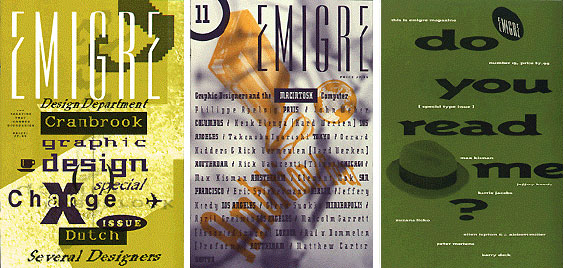
»Das Ende« von EmigreHeute erscheint zum 69. und letzten Mal das angesehene Designmagazin
»Emigre«, herausgegeben vom gleichnamigen Schriftenhaus –
FontShop war Emigre kurz nach seiner Gründung Ende der 80er Jahre das
Sprachrohr der grafischen Revolution. Wir erinnern uns an wegweisende
Leitartikel, einprägsame Cover und programmatische Poster ... und
natürlich die Schriften. Sie zählen bis heute zu den Bestsellern.
Die Emigre-Gründer Zuzana Licko und Rudy Vanderlans
schreiben uns in einer E-Mail zur letzten Ausgabe: »Alles hat einmal
ein Ende. Und nach 21 Jahren Emigre-Magazin ziehen wir beide uns zurück. Es
ist schon etwas traurig mit Nummer 60 die letzte Ausgabe anzukündigen. Eine
Meilenstein-Ausgabe: Wir blicken zurück auf die Geschichte unseres
Magazins, wobei uns viele Mitarbeiter und Kollegen Lebwohl sagen.
Es war eine großartige Erfahrung. Wir danken allen Lesern.« ![]() Die letzte Ausgabe des Emigre-Magazins, hier zu bestellen ... Die E-Mail endet mit den Worten: »Bitte beachten: Auch wenn wir das Erscheinen des Magazins beenden – Als Firma werden wir natürlich weiter bestehen. Es gibt noch viel zu tun.« ![]() Drei legendäre Emigre-Ausgaben aus der Zeit der Desktop-Publishing-Revolution Ende der 80er Jahre Herausgegeben: Di - November 8, 2005 at 09:00 vorm. | |